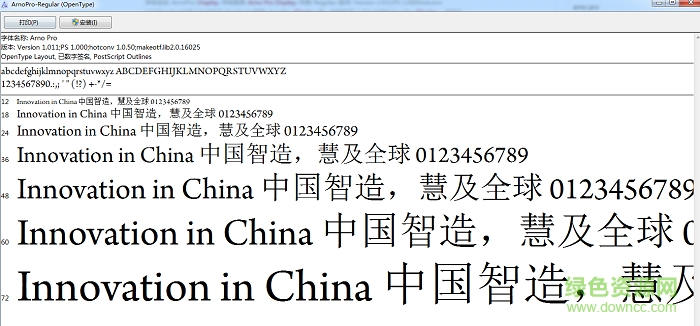
arno pro display-普通體
arno pro display 常規(guī)斜體是一款很有現(xiàn)代風格的英文襯線字體,可以用于網(wǎng)頁ui設計中,本站為大家免費提供arno pro display的常規(guī)普通體和斜體兩款字體的下載地址!
arno pro display-普通體